Top 20 font chữ cho thiết kế giáo dục, khóa học online và tài liệu học tập
Gợi ý 20 font TH Việt hóa dễ đọc cho thiết kế giáo dục, khóa học online, tài liệu học tập, giáo án, slide và poster tuyển sinh.
Thiết kế giáo dục có một yêu cầu rất rõ: đẹp nhưng phải dễ đọc. Dù bạn làm slide bài giảng, giáo án, worksheet, poster tuyển sinh, tài liệu PDF hay landing page khóa học online, font chữ cần giúp người học tiếp nhận thông tin nhanh hơn chứ không làm họ mỏi mắt.
Với tiếng Việt, chọn font giáo dục càng cần cẩn thận vì dấu phải rõ ở nhiều kích thước khác nhau. Một font cute có thể hợp trẻ em nhưng không nên dùng cho đoạn dài. Một font công nghệ có thể hợp khóa học AI nhưng chưa chắc phù hợp tài liệu học thuật. Vì vậy nên xây thư viện font theo nhóm nhu cầu.
Bài viết này gợi ý 20 font TH Việt hóa cho thiết kế giáo dục, khóa học online, e-learning và tài liệu học tập. Danh sách có cả font dễ đọc cho nội dung dài, font thân thiện cho trẻ em, font hiện đại cho khóa học công nghệ và font nổi bật cho poster tuyển sinh.
Tiêu chí chọn font giáo dục Việt hóa
Tiêu chí quan trọng nhất là độ đọc. Người học thường đọc trên màn hình laptop, điện thoại, máy chiếu hoặc bản in. Font cần có hình chữ rõ, khoảng cách thoáng và dấu tiếng Việt không bị dính vào chữ.
Tiêu chí thứ hai là đúng độ tuổi. Tài liệu mầm non, tiểu học có thể dùng font bo tròn, vui tươi. Tài liệu THCS, THPT, đại học hoặc khóa học chuyên môn nên dùng font sans-serif hoặc serif gọn, tránh quá trẻ con.
Tiêu chí thứ ba là đúng nền tảng. Slide PowerPoint cần font rõ khi chiếu xa; landing page khóa học cần font tạo độ tin cậy; worksheet cần font dễ đọc khi in; poster tuyển sinh cần font đủ nổi bật để thu hút.
Nên dùng font nào cho slide, giáo án và tài liệu học tập?
Với slide bài giảng, hãy dùng font dễ đọc cho nội dung chính và chỉ dùng font trang trí ở tiêu đề. Một slide có quá nhiều kiểu chữ sẽ làm học viên phân tâm.
Với giáo án hoặc tài liệu PDF, font nội dung nên ổn định, có độ đọc cao và không quá cá tính. Các phần tiêu đề, ví dụ, ghi chú hoặc hoạt động nhóm có thể dùng font thân thiện hơn để tạo nhịp đọc.
Với tài liệu trẻ em, font nên vui nhưng vẫn rõ. Các chữ có dấu như "ươ", "ă", "ê", "đ" cần được test kỹ vì trẻ nhỏ đang học đọc sẽ dễ bị nhầm nếu chữ quá trang trí.
Top 20 font chữ cho thiết kế giáo dục, khóa học online và tài liệu học tập
Các font dưới đây được chọn theo nhiều tình huống thiết kế giáo dục khác nhau. Bạn có thể dùng font tiêu đề để tạo cảm xúc, sau đó phối với font dễ đọc hơn cho nội dung dài.
1. TH Algance
TH Algance là sans serif tối giản, dễ đọc, phù hợp slide bài giảng, tài liệu PDF, giáo án, workbook và các khóa học online cần cảm giác chuyên nghiệp. Khi dùng cho giáo dục, hãy test thử tiêu đề bài học, một đoạn nội dung ngắn và vài từ có dấu để đảm bảo font dễ đọc trên màn hình và bản in.
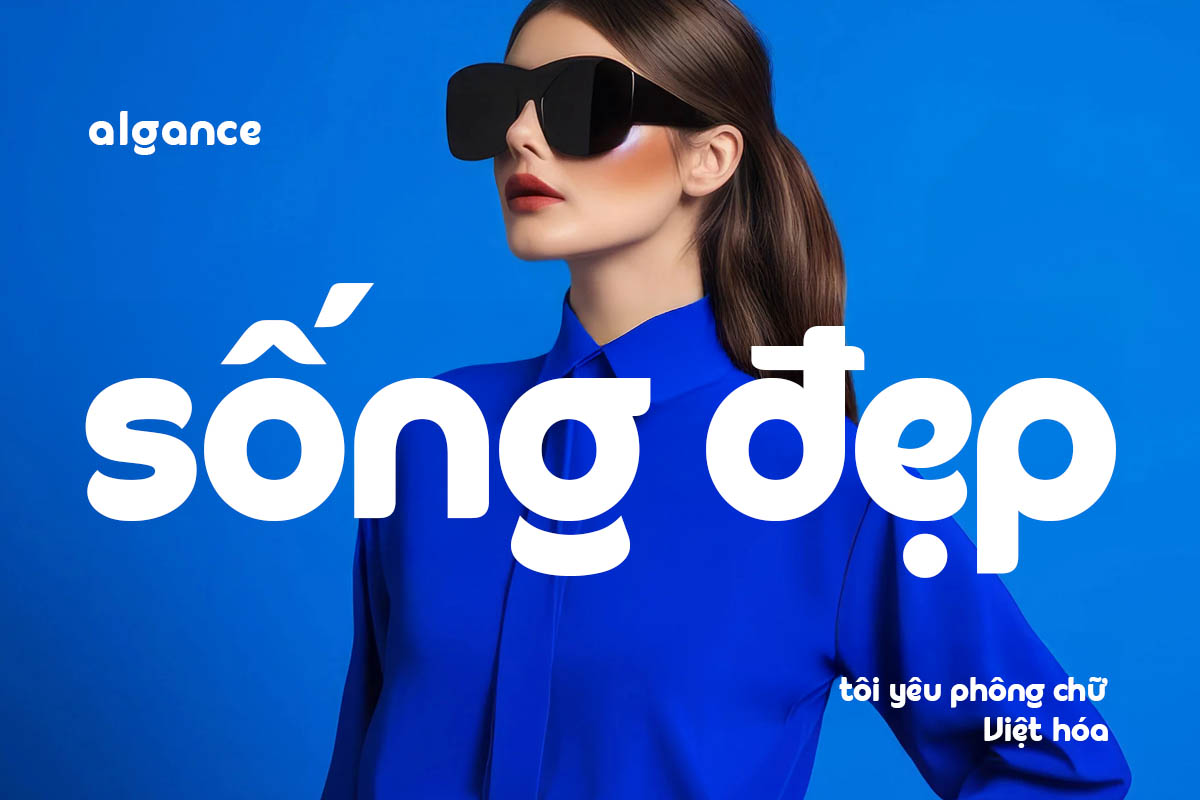
2. TH Bagyo Sans
TH Bagyo Sans là font bo tròn vui nhộn, hợp tài liệu trẻ em, worksheet, flashcard, poster lớp học sáng tạo và thiết kế mầm non/tiểu học. Khi dùng cho giáo dục, hãy test thử tiêu đề bài học, một đoạn nội dung ngắn và vài từ có dấu để đảm bảo font dễ đọc trên màn hình và bản in.
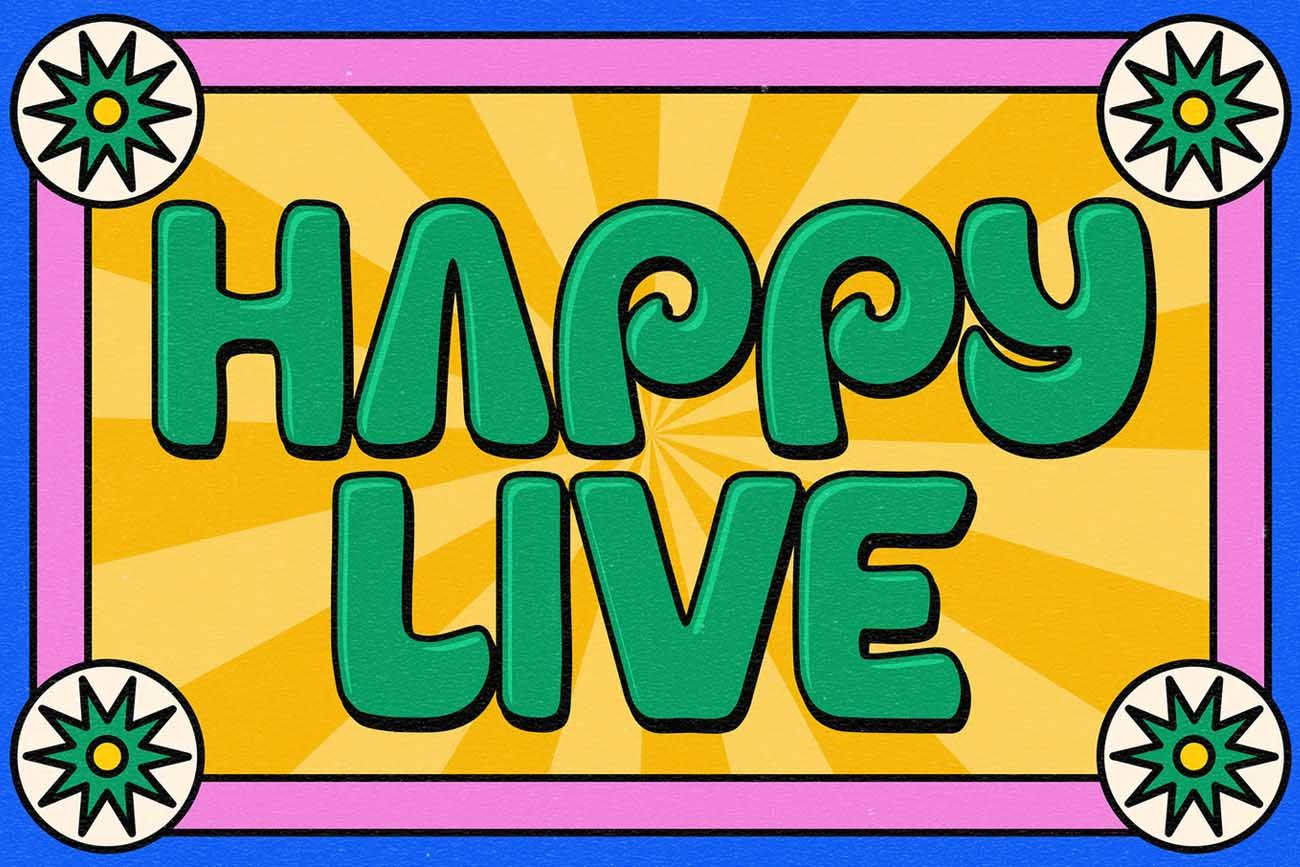
3. TH More Sugar
TH More Sugar là font hoạt hình vui nhộn, phù hợp banner lớp học thiếu nhi, bài tập tô màu, poster trung tâm kỹ năng và nội dung giáo dục giải trí. Khi dùng cho giáo dục, hãy test thử tiêu đề bài học, một đoạn nội dung ngắn và vài từ có dấu để đảm bảo font dễ đọc trên màn hình và bản in.
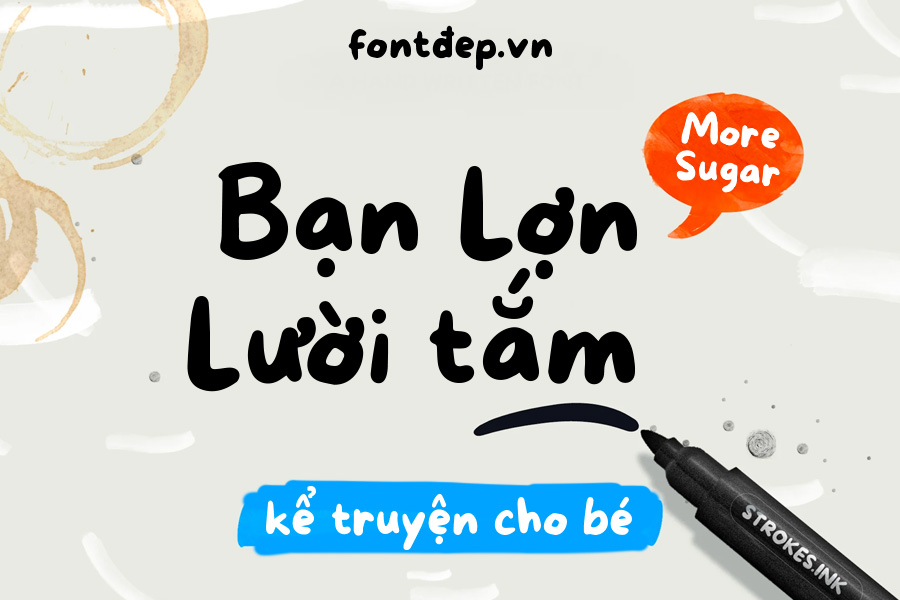
4. TH Playful Bubble
TH Playful Bubble là font bubble đáng yêu, hợp slide trẻ em, tiêu đề trò chơi học tập, bài đăng lớp tiếng Anh thiếu nhi và cover video giáo dục vui. Khi dùng cho giáo dục, hãy test thử tiêu đề bài học, một đoạn nội dung ngắn và vài từ có dấu để đảm bảo font dễ đọc trên màn hình và bản in.
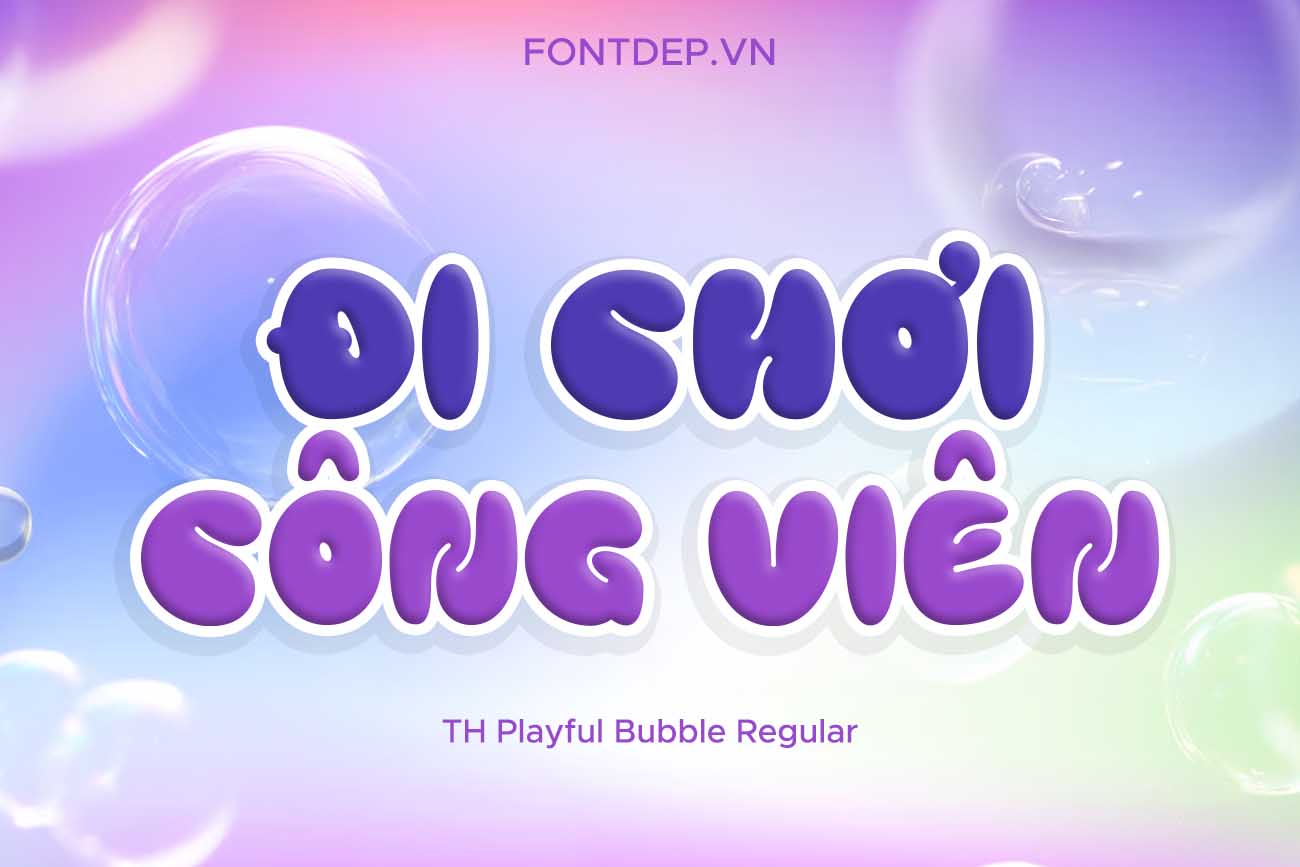
5. TH Cherry Feeling
TH Cherry Feeling là font viết tay dễ thương, phù hợp worksheet, thiệp khen thưởng, nhãn lớp học, bài social giáo viên và tài liệu học tập thân thiện. Khi dùng cho giáo dục, hãy test thử tiêu đề bài học, một đoạn nội dung ngắn và vài từ có dấu để đảm bảo font dễ đọc trên màn hình và bản in.
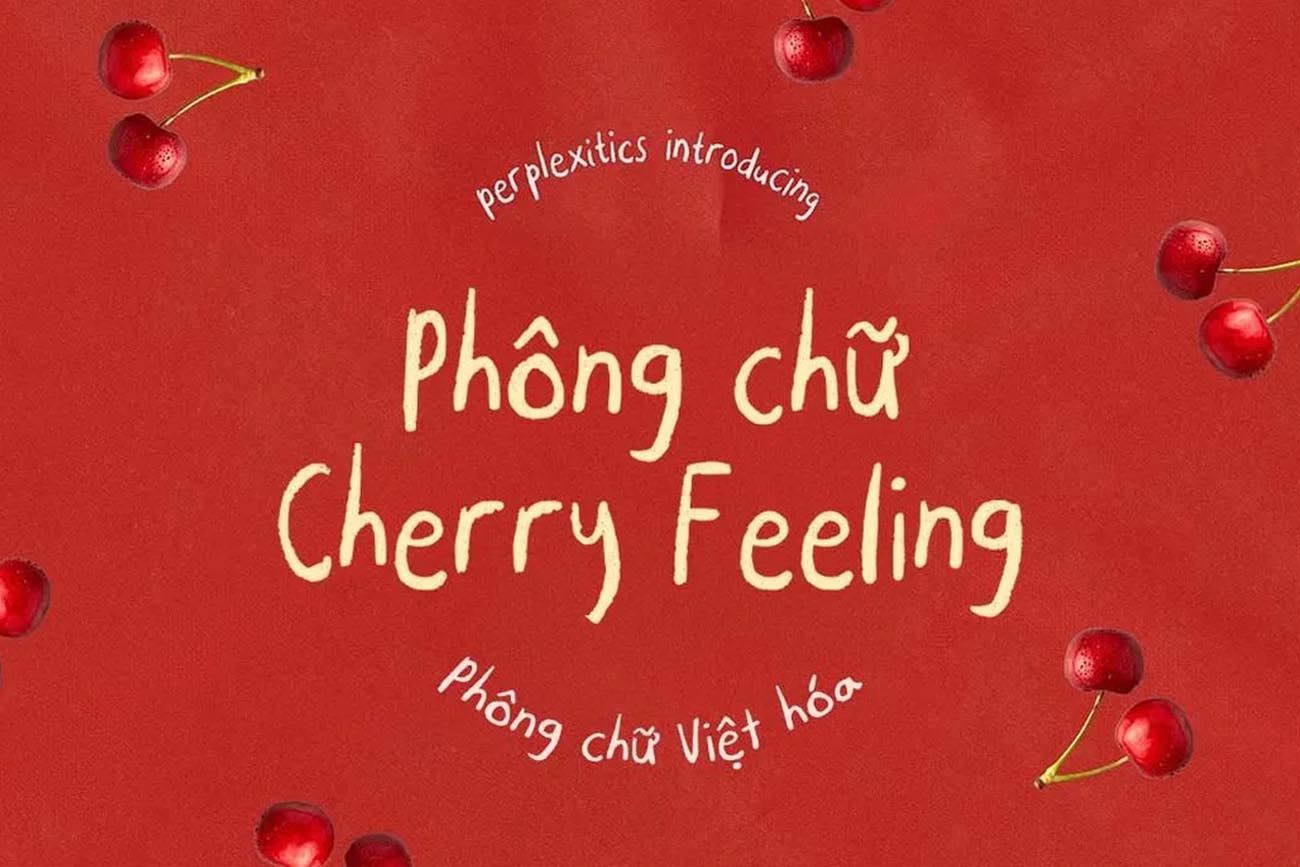
6. TH Glafty
TH Glafty là font vui tươi năng động, hợp poster khóa học hè, lớp kỹ năng, câu lạc bộ, workshop sáng tạo và banner tuyển sinh trẻ em. Khi dùng cho giáo dục, hãy test thử tiêu đề bài học, một đoạn nội dung ngắn và vài từ có dấu để đảm bảo font dễ đọc trên màn hình và bản in.
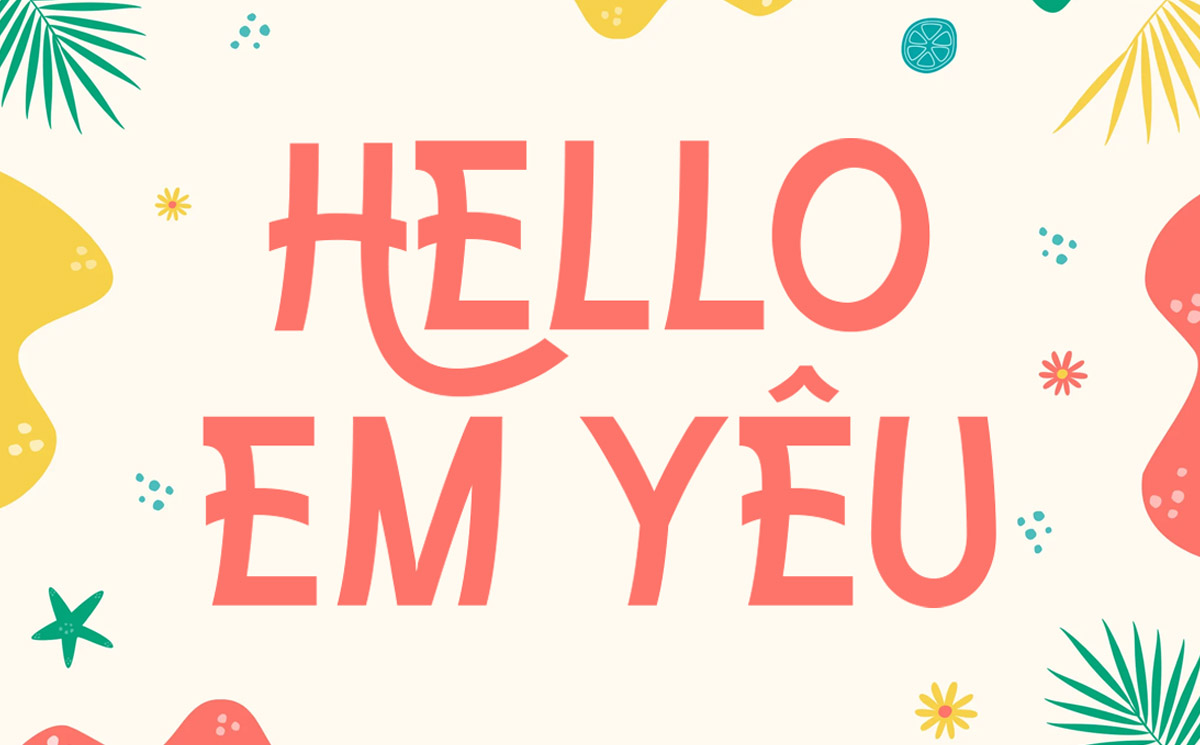
7. TH Mighty Kingdom
TH Mighty Kingdom là font mũm mĩm dễ thương, phù hợp thiết kế giáo dục mầm non, sticker, bảng nội quy lớp học và tài liệu học qua trò chơi. Khi dùng cho giáo dục, hãy test thử tiêu đề bài học, một đoạn nội dung ngắn và vài từ có dấu để đảm bảo font dễ đọc trên màn hình và bản in.
Tải font: tải font TH Mighty Kingdom
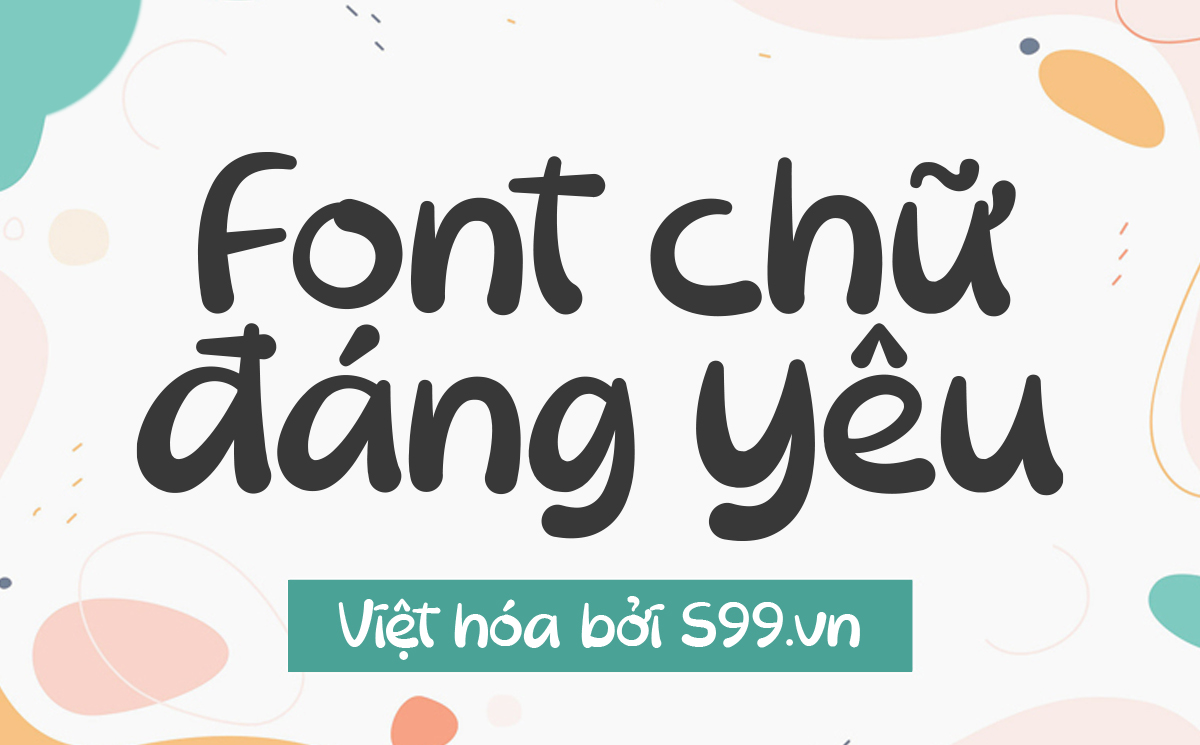
8. TH Giabe
TH Giabe là sans serif display hiện đại, hợp landing khóa học, poster tuyển sinh, cover webinar, bài quảng cáo khóa học và thương hiệu giáo dục trẻ. Khi dùng cho giáo dục, hãy test thử tiêu đề bài học, một đoạn nội dung ngắn và vài từ có dấu để đảm bảo font dễ đọc trên màn hình và bản in.
Tải font: tải font TH Giabe
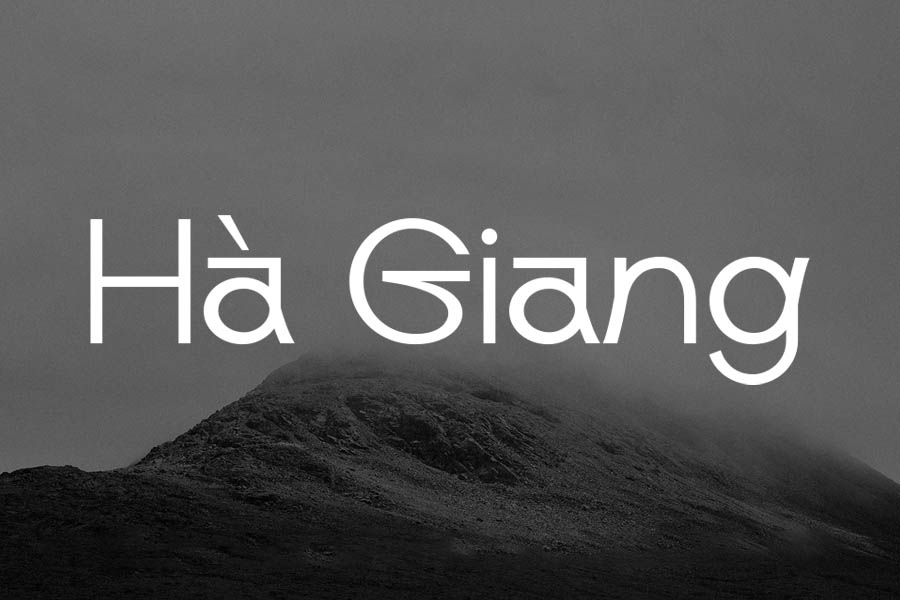
9. TH Belly & Park
TH Belly & Park là font condensed hiện đại, tiết kiệm diện tích cho poster tuyển sinh, banner workshop, cover khóa học và thumbnail bài giảng. Khi dùng cho giáo dục, hãy test thử tiêu đề bài học, một đoạn nội dung ngắn và vài từ có dấu để đảm bảo font dễ đọc trên màn hình và bản in.
Tải font: tải font TH Belly & Park
10. TH Geardive
TH Geardive là font thể thao tương lai, hợp khóa học công nghệ, e-sport, robotics, STEM, poster cuộc thi và nội dung học tập năng lượng cao. Khi dùng cho giáo dục, hãy test thử tiêu đề bài học, một đoạn nội dung ngắn và vài từ có dấu để đảm bảo font dễ đọc trên màn hình và bản in.
Tải font: tải font TH Geardive
11. TH Axiome
TH Axiome là font công nghệ tối giản, hợp khóa học AI, lập trình, tin học, UI/UX, sản phẩm số và landing page e-learning. Khi dùng cho giáo dục, hãy test thử tiêu đề bài học, một đoạn nội dung ngắn và vài từ có dấu để đảm bảo font dễ đọc trên màn hình và bản in.
Tải font: tải font TH Axiome
12. TH Seona Display
TH Seona Display là font công nghệ nổi bật, phù hợp webinar công nghệ, bootcamp lập trình, poster workshop và thumbnail bài học kỹ thuật. Khi dùng cho giáo dục, hãy test thử tiêu đề bài học, một đoạn nội dung ngắn và vài từ có dấu để đảm bảo font dễ đọc trên màn hình và bản in.
Tải font: tải font TH Seona Display
13. TH Gyokz
TH Gyokz là font công nghệ hiện đại, hợp thiết kế khóa học game, AI, cyber security, robotics và các chủ đề STEM cần cảm giác mạnh. Khi dùng cho giáo dục, hãy test thử tiêu đề bài học, một đoạn nội dung ngắn và vài từ có dấu để đảm bảo font dễ đọc trên màn hình và bản in.
Tải font: tải font TH Gyokz
14. TH Revans Serif
TH Revans Serif là serif cổ điển hiện đại, phù hợp tài liệu học thuật, bìa giáo trình, chứng chỉ, proposal khóa học và thiết kế giáo dục cao cấp. Khi dùng cho giáo dục, hãy test thử tiêu đề bài học, một đoạn nội dung ngắn và vài từ có dấu để đảm bảo font dễ đọc trên màn hình và bản in.
Tải font: tải font TH Revans Serif
15. TH Selvia Genatu
TH Selvia Genatu là serif sang trọng, hợp bìa ebook, khóa học nghệ thuật, tài liệu thương hiệu cá nhân, chứng nhận và profile giảng viên. Khi dùng cho giáo dục, hãy test thử tiêu đề bài học, một đoạn nội dung ngắn và vài từ có dấu để đảm bảo font dễ đọc trên màn hình và bản in.
Tải font: tải font TH Selvia Genatu
16. TH This Reality
TH This Reality là font viết tay mềm mại, hợp quote học tập, slide truyền cảm hứng, bài social giáo dục và tiêu đề phụ thân thiện. Khi dùng cho giáo dục, hãy test thử tiêu đề bài học, một đoạn nội dung ngắn và vài từ có dấu để đảm bảo font dễ đọc trên màn hình và bản in.
Tải font: tải font TH This Reality
17. TH Bonitte
TH Bonitte là script retro viết tay, phù hợp khóa học handmade, mỹ thuật, nấu ăn, nhật ký học tập và các thiết kế có cảm giác thủ công. Khi dùng cho giáo dục, hãy test thử tiêu đề bài học, một đoạn nội dung ngắn và vài từ có dấu để đảm bảo font dễ đọc trên màn hình và bản in.
Tải font: tải font TH Bonitte
18. TH Kinetic Motion
TH Kinetic Motion là brush mạnh mẽ, hợp poster workshop, cuộc thi, khóa học thể thao, bootcamp hoặc các chương trình cần tạo cảm giác hành động. Khi dùng cho giáo dục, hãy test thử tiêu đề bài học, một đoạn nội dung ngắn và vài từ có dấu để đảm bảo font dễ đọc trên màn hình và bản in.
Tải font: tải font TH Kinetic Motion
19. TH Roge
TH Roge là display retro, hợp poster lớp nhạc, mỹ thuật, văn hóa, câu lạc bộ, workshop sáng tạo và tài liệu có phong cách vintage. Khi dùng cho giáo dục, hãy test thử tiêu đề bài học, một đoạn nội dung ngắn và vài từ có dấu để đảm bảo font dễ đọc trên màn hình và bản in.
Tải font: tải font TH Roge
20. TH Colombo Sans
TH Colombo Sans là font hoài cổ gọn, phù hợp tài liệu lịch sử, văn hóa, lớp kỹ năng sống, poster câu lạc bộ và nội dung giáo dục có màu sắc truyền thống. Khi dùng cho giáo dục, hãy test thử tiêu đề bài học, một đoạn nội dung ngắn và vài từ có dấu để đảm bảo font dễ đọc trên màn hình và bản in.
Tải font: tải font TH Colombo Sans
-20250815-085336.jpg)
Gợi ý chọn font theo từng loại tài liệu giáo dục
Nếu làm giáo án, tài liệu PDF hoặc workbook, hãy ưu tiên TH Algance, TH Revans Serif hoặc TH Selvia Genatu cho cấu trúc rõ ràng. Những font này phù hợp nội dung cần đọc lâu và giữ cảm giác chỉn chu.
Nếu làm tài liệu trẻ em, flashcard hoặc poster lớp học vui, TH Bagyo Sans, TH More Sugar, TH Playful Bubble, TH Cherry Feeling, TH Glafty và TH Mighty Kingdom sẽ thân thiện hơn. Dù vậy, hãy dùng chúng chủ yếu cho tiêu đề hoặc hoạt động ngắn.
Nếu làm khóa học online về công nghệ, STEM, AI, lập trình hoặc e-sport, TH Axiome, TH Seona Display, TH Gyokz và TH Geardive sẽ tạo cảm giác hiện đại. Hãy phối thêm font dễ đọc cho nội dung bài học.
Checklist trước khi xuất slide, giáo án và poster tuyển sinh
Hãy xem thử thiết kế trên đúng thiết bị sử dụng. Slide cần kiểm tra trên máy chiếu hoặc màn hình nhỏ; tài liệu PDF cần in thử vài trang; landing page khóa học cần xem trên điện thoại.
Kiểm tra dấu tiếng Việt trong các từ như "khóa học", "tài liệu", "giáo án", "trải nghiệm", "học viên", "đăng ký". Nếu dấu quá sát hoặc quá nhỏ, hãy đổi font hoặc tăng kích thước chữ.
Đừng dùng quá nhiều font trong một bộ tài liệu. Một khóa học online nên có bộ font cố định cho tiêu đề, nội dung, ghi chú và CTA. Điều này giúp thương hiệu khóa học nhất quán và dễ tin cậy hơn.
Font giáo dục Việt hóa cần dễ đọc, đúng độ tuổi, đúng nền tảng và hỗ trợ tiếng Việt ổn định. Với tài liệu học tập, độ rõ quan trọng hơn sự cầu kỳ. Với poster tuyển sinh hoặc khóa học online, font có thể nổi bật hơn nhưng vẫn phải giữ được sự tin cậy.
20 font TH Việt hóa trong bài là bộ gợi ý thực tế để bạn thiết kế slide, giáo án, tài liệu học tập, poster tuyển sinh và landing page e-learning. Hãy chọn font theo mục tiêu học tập, test trên nội dung thật và lưu thành bộ font riêng cho từng nhóm khóa học.